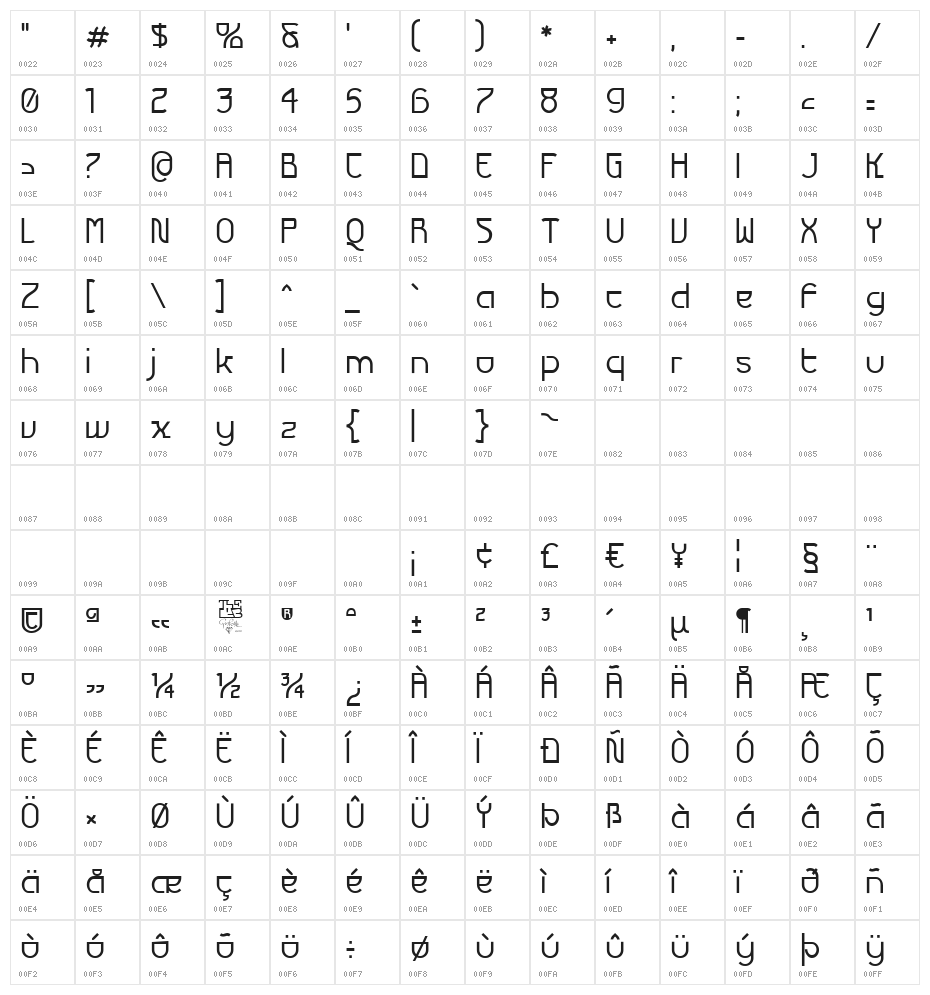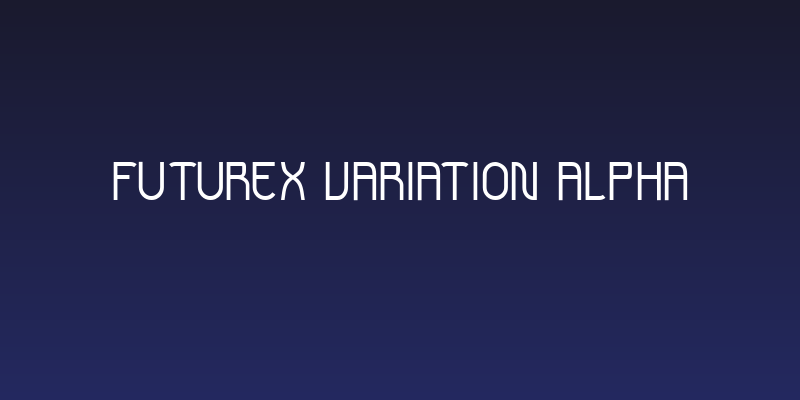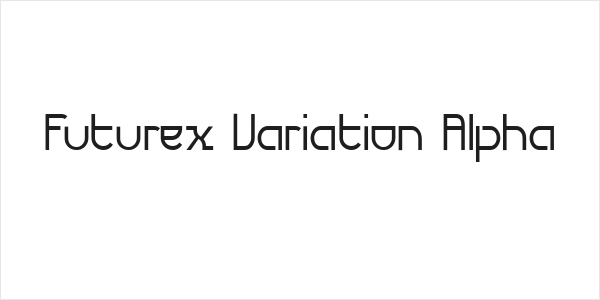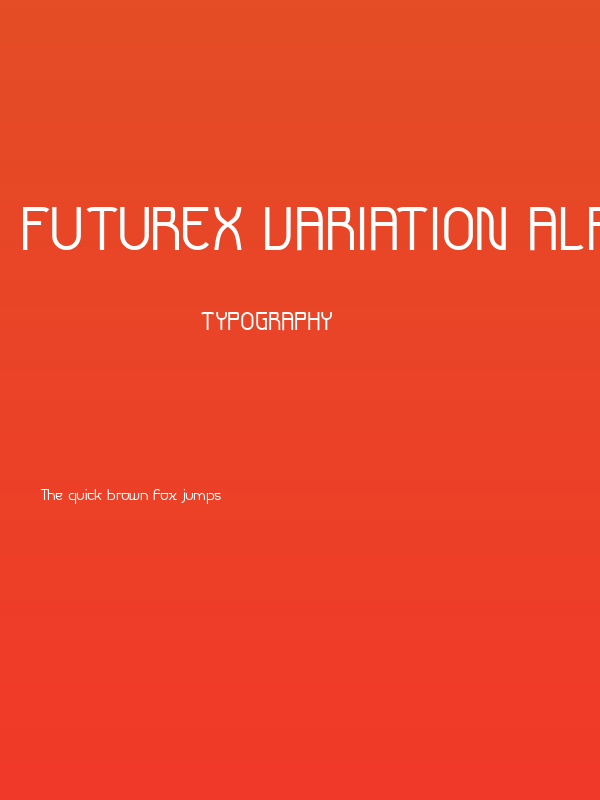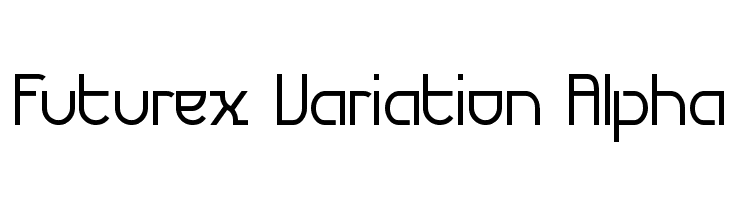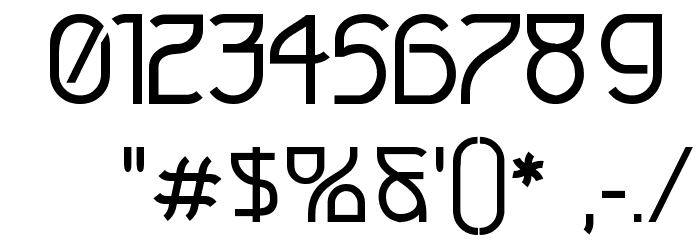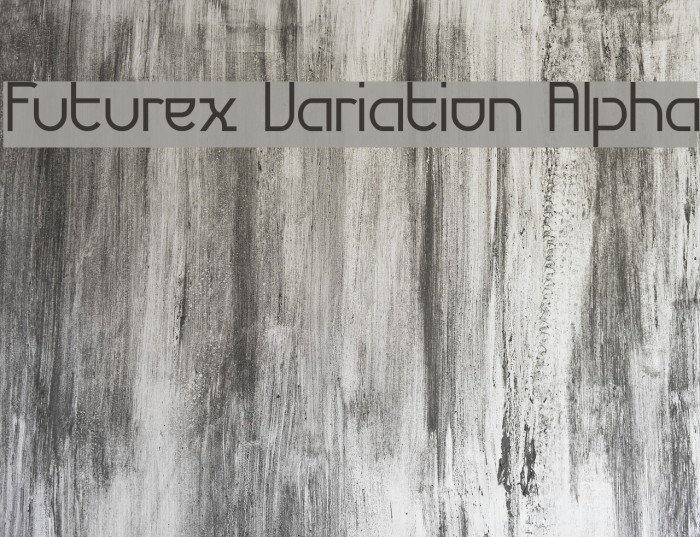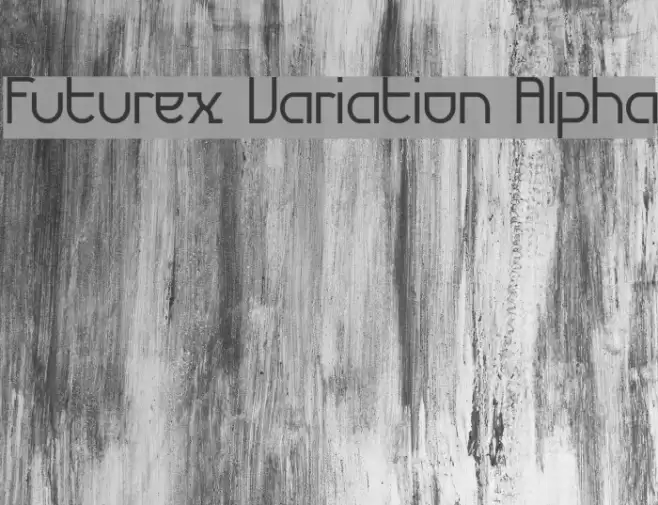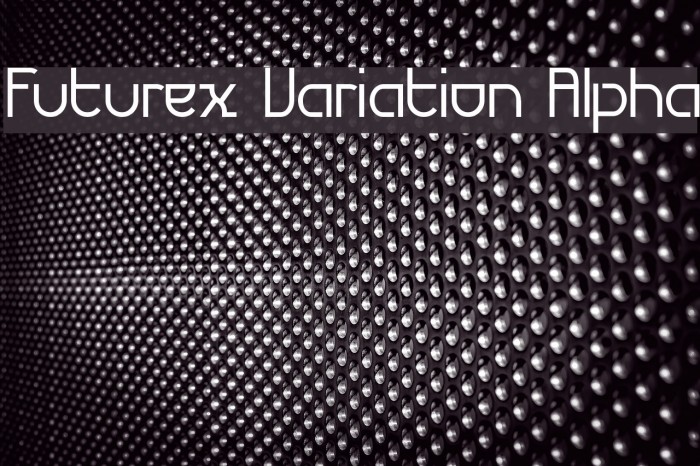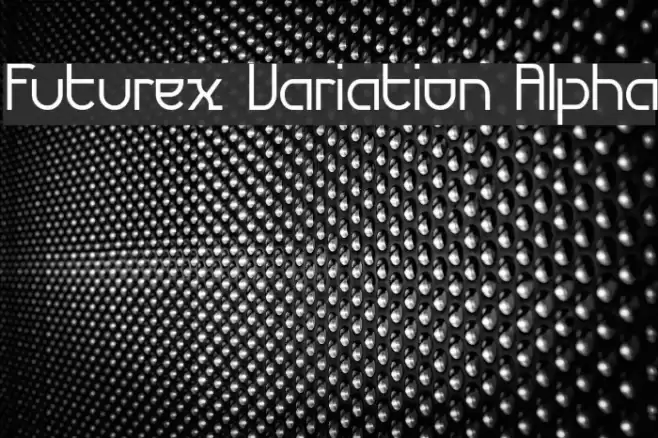
Futurex Variation Alpha Font
Fonts by Apostrophic Lab
| Название | Futurex Variation Alpha |
| Категория | Futuristic |
| Рекомендуемые проекты | Ideal for technology branding, futuristic posters, and innovative product packaging. |
| Автор | Fonts by Apostrophic Lab |